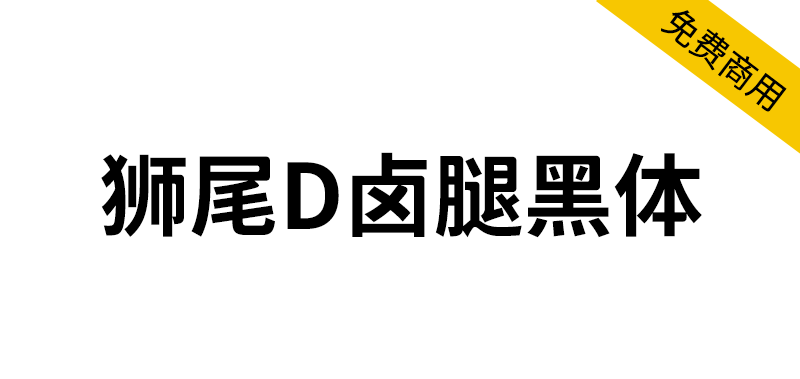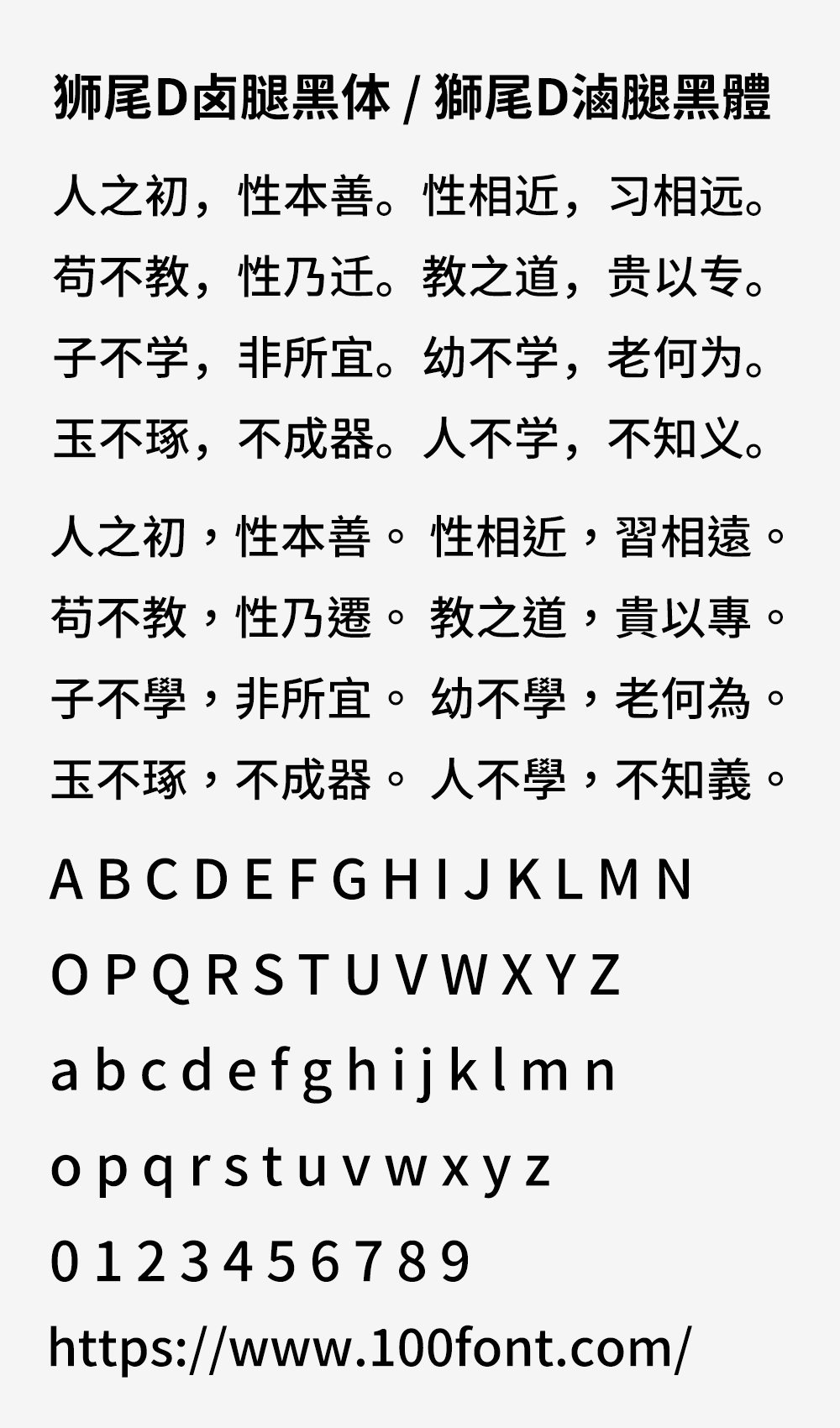
狮尾D卤腿黑体基于思源黑体的右侧变圆改造,更加简明现代化的字体。和思源黑体一样,有7种字重,支持简体中文、繁体中文、韩文与日文,可以免费商用,欢迎大家自由应用、自由优化、自由改作!
狮尾D卤腿黑体与「狮尾德鲁纳黑体」差别在有没有拔脚,「拔脚」就是会有较少的笔画,例如移除「口」字的左右下角会多出的短线条。有拔脚的字会较圆,但是会造成有些字因直接去掉腿后左右不平衡、左右不对衬的「悬空」问题。改使用「腿」系列字体就不会有这个问题。